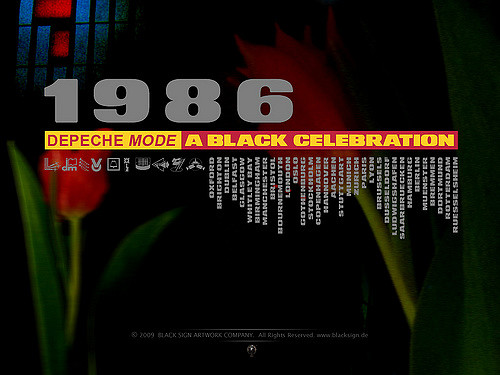
Suche Schrift von Albumcover - Black Celebration
Ich suche die Schrift bzw. Schriften - sowohl von "Depeche Mode", als auch "Black Celebration". Die gängigen Erkennungstools konnten mir nicht weiterhelfen.
Komisch, dass da als Datum 2009 angegeben ist, das Artwork ist ja von 1986.
und bei den Erkennungstools die Schrift wirklich von jeder Art Grafik befreien, und die Schriftarten auch vereinzeln, sodass wirklich am besten schwarze Schrift auf weißem Grund übreig bleibt, die nur aus einer Schriftart bestehtm, bei DEPECHE MODE sogar das DEPECHE vom kursiven MODE trennen.